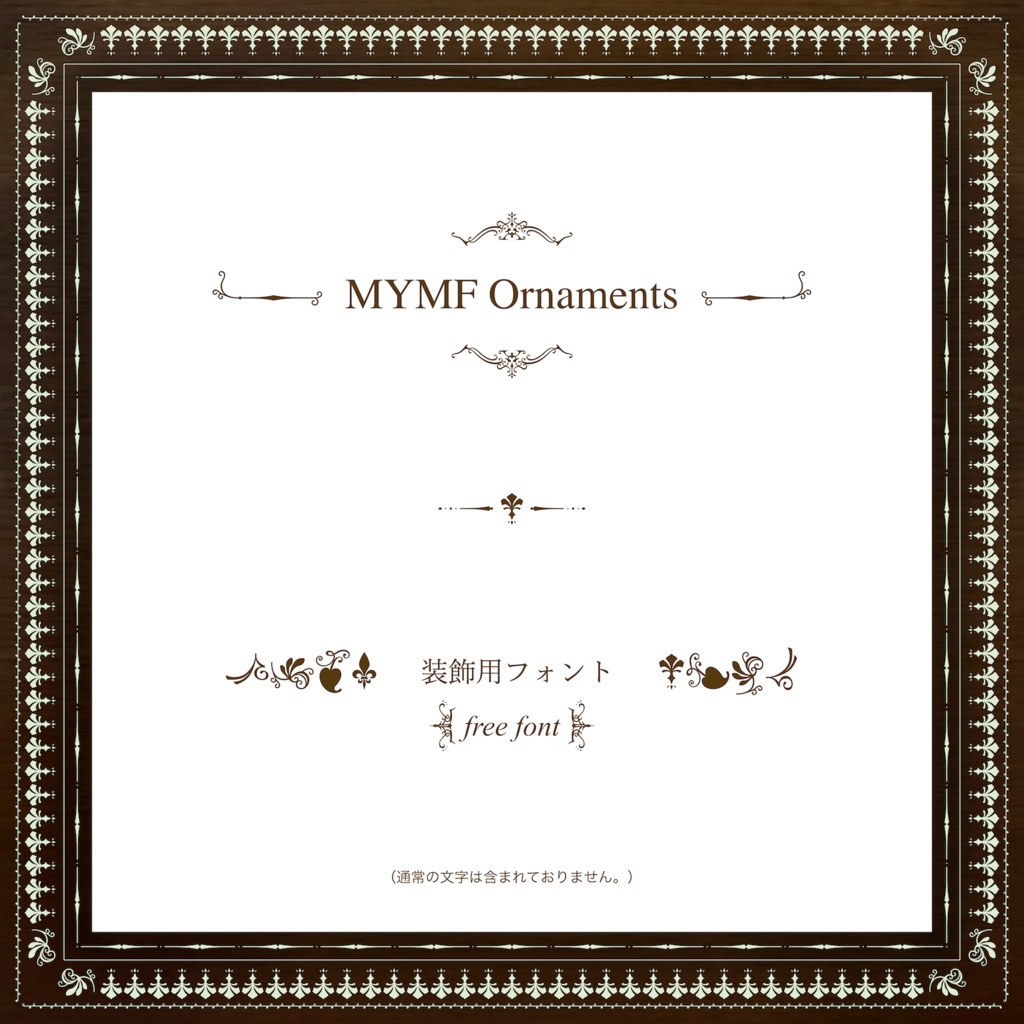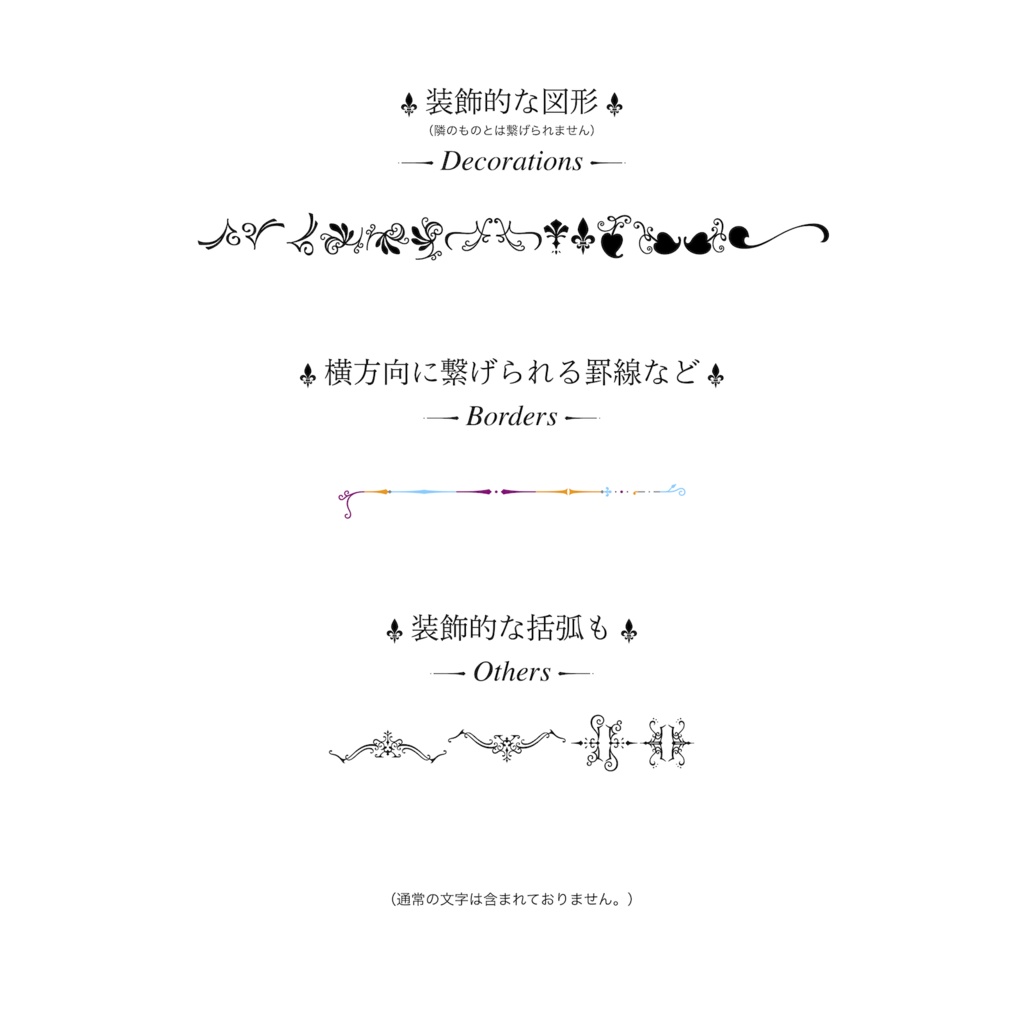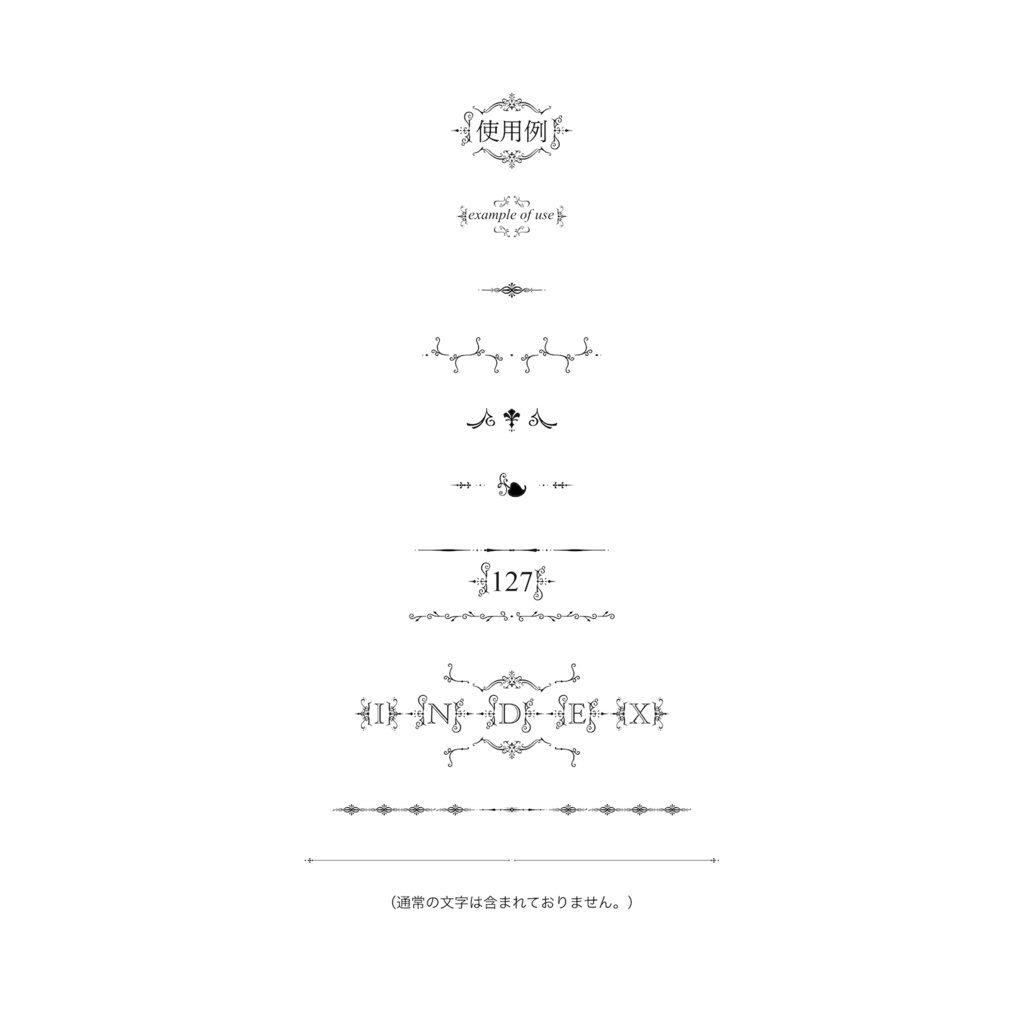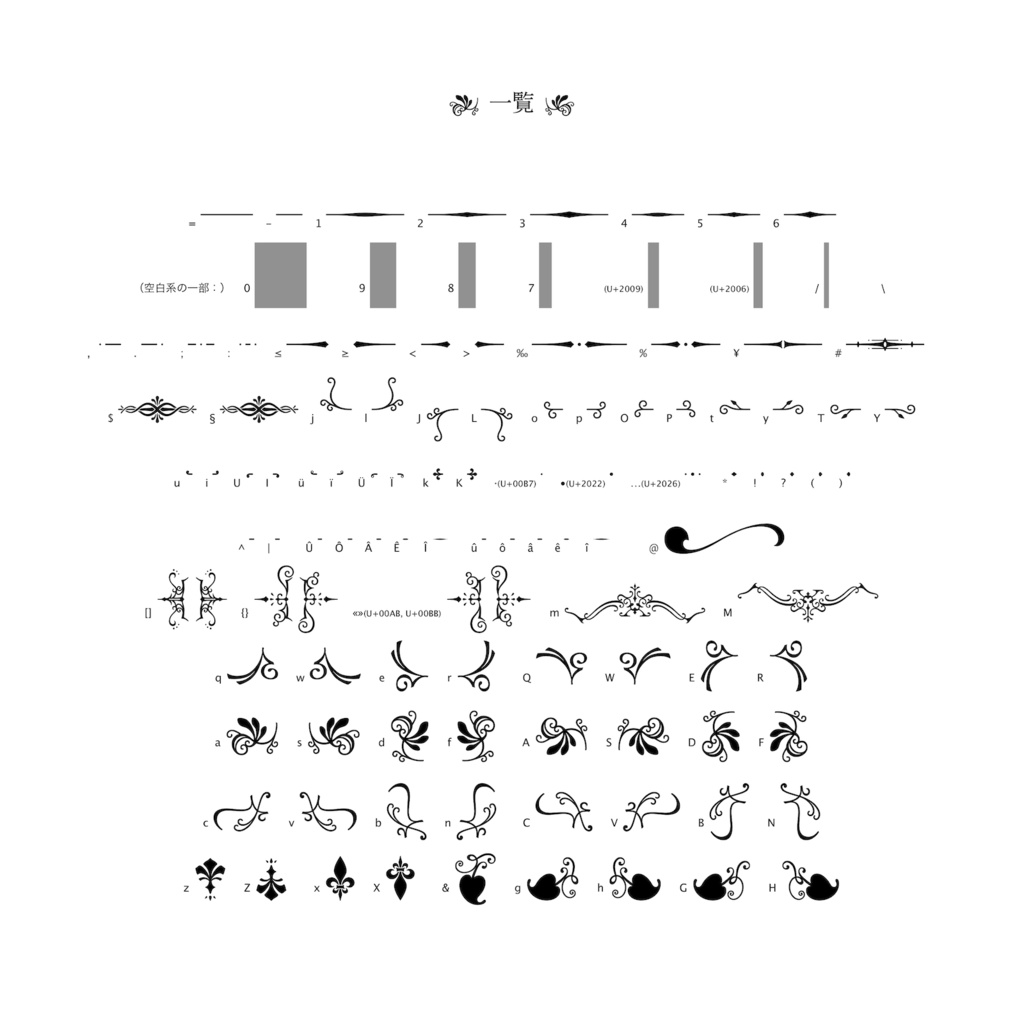
【フリーフォント】MYMF Ornaments
通常の文字の代わりに、装飾的な図形などを入力できるフォントを作ってみました。 多くは1,2,3やa,b,cなどの基本的な文字に割り当ててあります。似たような図形がQWERTY配列(一般的なキーボードの並び順)で近くなるようにしているので入力しやすいです。 通常の文字は入っていないので、文章などを入れる場合は他のフォント等と組み合わせて使う形になります。 ライセンスは SIL Open Font License Version 1.1 を採用しています。商用利用や組み込みは可となります。 ・罫線系 横向きの直線など。横に並べると各図形が繋がるようになっています。(変形するわけではなく、元々繋がるような形で作ってあります。) ・図案系 計8種類の図案と、その向きなどが違うバリエーション(最大で計8パターン)。こちらは横に並べても繋がりません。6種のオリジナルの図案と、フルール・ド・リス、フルーロンになります。 ・装飾的な括弧 2種類の装飾的な括弧が3対入っています。 これらの他に、7種類の幅の空白を入れてあり、うち5種類は数字などの打ちやすい文字に割り当てているので、簡単にある程度の位置調整が出来るようになっています。 TrueTypeフォントの他に、webフォント版(woff)、文字への割り当てや簡単な説明を書いたPDFなどを同梱しています。 割り当てられている文字一覧 =-—–123456,.;:≤≥<>‰%¥#$§jlJLopOPtyTYuiUIüïÜÏkK·•…*!?()^|ÛÔÂÊÎûôâêî0987/\ qwerQWERasdfASDFcvbnCVBNzZxX&ghGH@⚜❦❧☙mM[]{}«» 2024年4月10日 Version 1.0.0 公開 このフォントの紹介はご自由にどうぞ。その際ここに示した文章や画像はご自由にお使い下さって構いません。